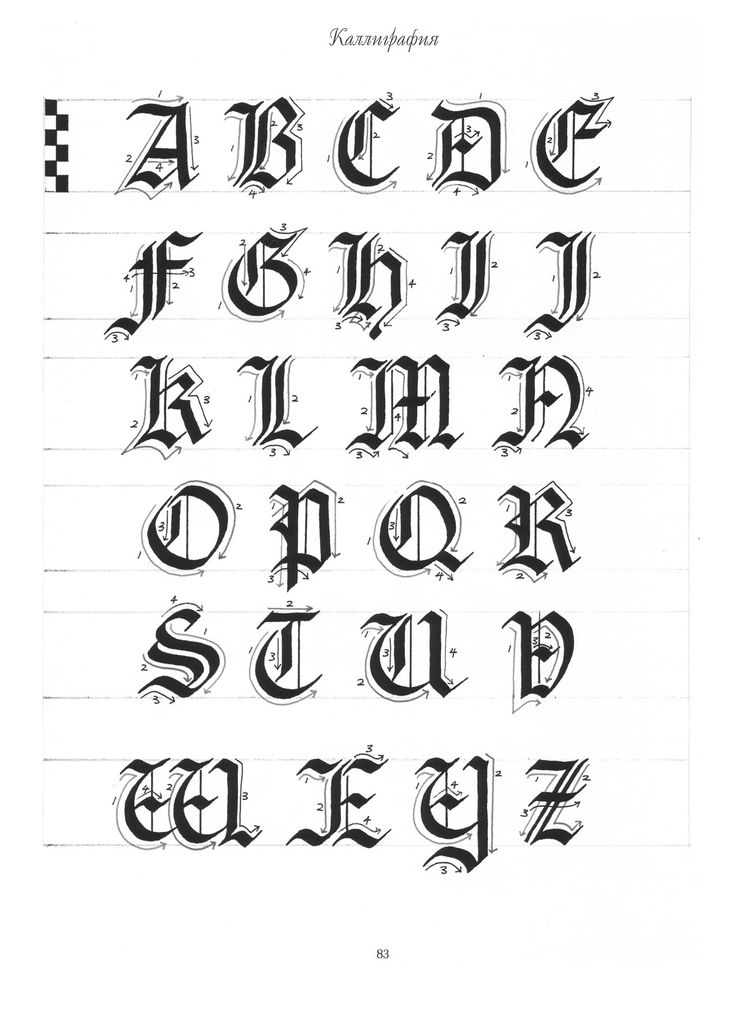
Красивый шрифт для тату на латыни (48 фото)
Как здорово, когда целая мысль заключена в одной фразе, а иногда целый мир в одном слове!
И вам непременно хочется отобразить это в виде временной татуировки на теле?
Здесь вы можете подобрать собственный шрифт для тату надписи.
*Обращаем внимание: не все латинские шрифты поддерживают кириллицу и наоборот =)
11 отличных шрифтов для татуировок
Татуировки с надписями
Татуировки с надписями очень популярны, и, наряду с цветом и дизайном, еще один способ добавить особый штрих к этим татуировкам с надписями – это выбрать из множества различных стилей доступных шрифтов для татуировок .
Некоторые из наиболее популярных и подходящих шрифтов для татуировок для разных стилей надписей будут рассмотрены ниже.
Шрифт Abbeyline — один из шрифтов семейства каллиграфических. Этот шрифт очень подходит для надписей на татуировках, которые имеют более серьезное значение. Имена ваших детей, духовные цитаты, библейские цитаты будут отлично смотреться в этом шрифте.
Выбирая шрифты для своих татуировок, вы должны учитывать удобочитаемость. Этот шрифт называется Gringo Nights. Как видите, это немного сложно читать, но при определенных обстоятельствах это было бы абсолютно уместно. Представьте этот шрифт под мультяшной татуировкой в стиле койота или, возможно, даже с племенной татуировкой.
Этот шрифт называется китайский на вынос. Это один из самых легко читаемых шрифтов в азиатском стиле для татуировок. Если вы хотите использовать азиатские шрифты в своих татуировках с надписями, но не настоящие японские или китайские иероглифы, это будет отличный шрифт.
Этот шрифт называется 256 байт. Для вас, компьютерных фанатов, а в наши дни многие просят татуировки, это может быть шрифт для вашей татуировки. Он жирный, удобочитаемый и будет отлично смотреться со всем, что связано с компьютером. Изображение находится под татуировкой со штрих-кодом или с любой поговоркой, имеющей отношение к технологическому миру.
Для любителей латинских изречений этот шрифт называется Justinian. ad honorem, например, означает «в честь» и является примером использования этого шрифта для латинских фраз.
Для вас, поклонников отвратительного, ужасного, готического и просто страшного боди-арта, который требует надписи в татуировке, это потрясающий шрифт. Называется Pillbox Opaque. Немного сложно читать, но как только вы к этому привыкнете; не так уж и плохо. Это также было бы хорошим шрифтом для практикующих виккан.
Все шрифты могут быть добавлены в цвет или окрашены в цвет, но шрифт особенно хорошо подходит для цвета. Этот шрифт называется Yold Angelican. Для впечатляюще сложных татуировок, относящихся к той эпохе, или для татуировок с надписями, которые включают цитаты из этой эпохи, более короткая цветная цитата с этим черным контуром будет отлично смотреться!